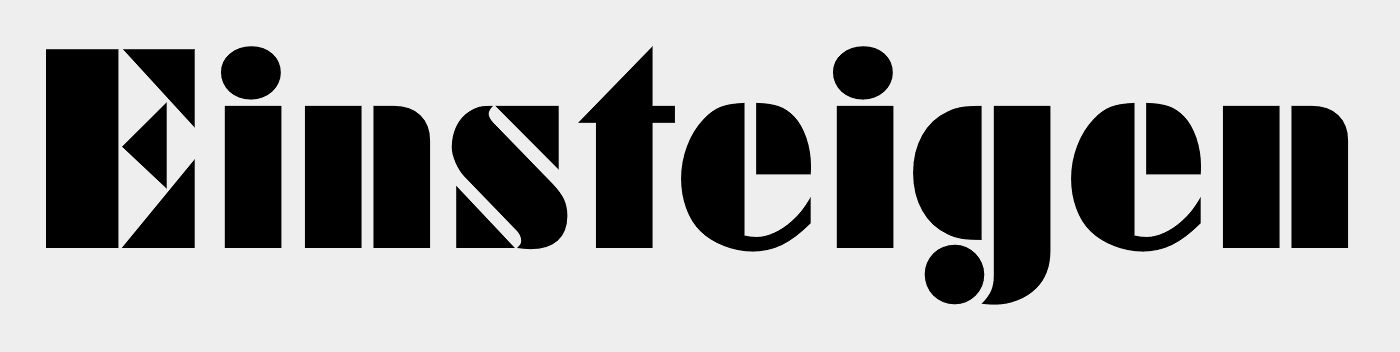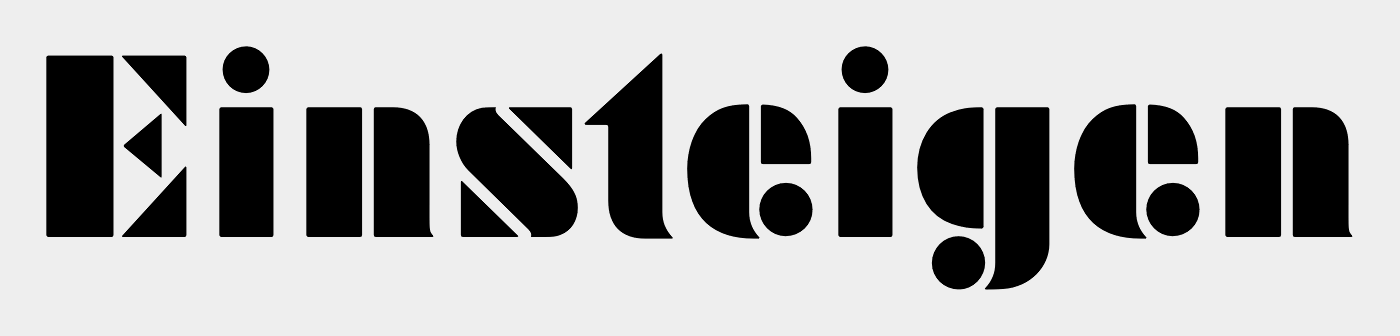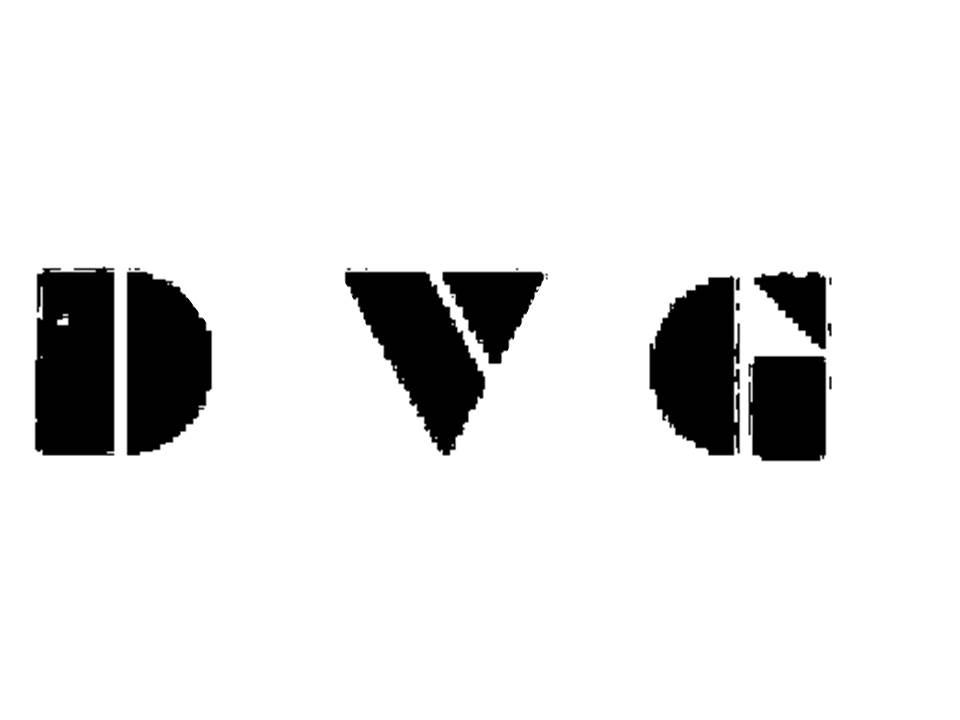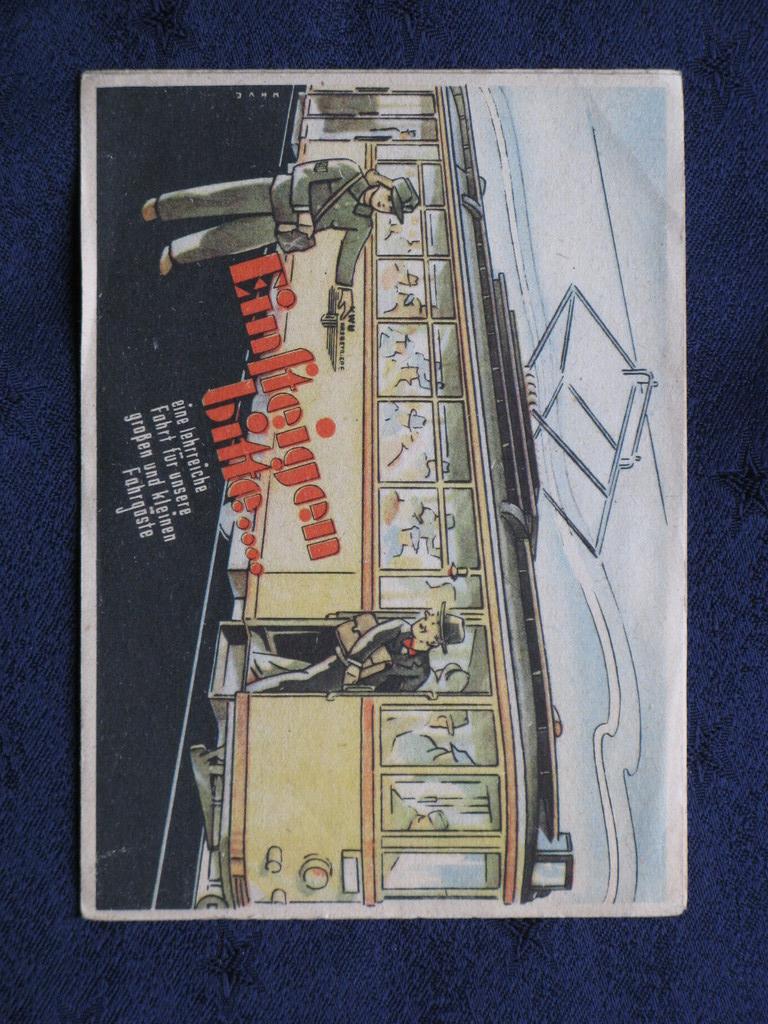
DDR-Font der 50er Jahre der Dresdner Verkehrbetriebe
ich bin auf der Suche nach der Schriftart, welche im Bild unten fuer "Einsteigen bitte" verwendet wurde bzw fuer die Abkuerzung "Dresdner Verkehrsgesellschaft".
Hallo Ralf, vielen Dank fuer Deine Hilfe. Vermutlich war in den fruehen 50ern ein Designer (Schriftgestalter am Werk) und kein Bleisatz im Einsatz. Ich danke Dir sehr.